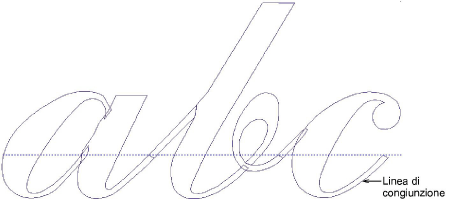
Digitalizza le lettere
Usa Digitalizzazione tradizionale > Colonna A per digitalizzare colonne in larghezza ed angolo punto variabili. Clicca a destra per impostazioni.
Usa Punti riempimento > Satin per applicare punto satin a colonne strette e sagome nuove o selezionate. Clicca a destra per impostazioni.
Utilizza Punti profilo > Satin per creare bordi più spessi o colonne di spessore uniforme. Clicca a destra per impostazioni.
Digitalizza lettere come già fatto per l’alfabeto personalizzato. Per tipi di caratteri in corsivo, la coda di ogni lettera deve coincidere con il tratto iniziale della prossima allo scopo di creare una giuntura ininterrotta. Trascina una linea guida in posizione per contrassegnare la ‘linea di congiunzione’.
Trascina una linea guida affinchè si intersechi con la linea di congiunzione nel margine interno del tratto. Attiva ‘Passa su Guide’ nel tab Opzioni > Griglia e guide. Assicurati che i punti di riferimento di lettere adiacenti coincidano con questo punto.
Il bordo della giuntura dovrebbe essere approssimativamente perpendicolare al tratto inclinato. Non è necessarila la sovrapposizione su tratti stretti poichè la compensazione tiro fornirà una sovrapposizione sufficiente.
Non preoccuparti dei punti di connessione fra gli oggetti. EmbroideryStudio lo fa automaticamente quando salvi con il metodo Giuntura più vicina.